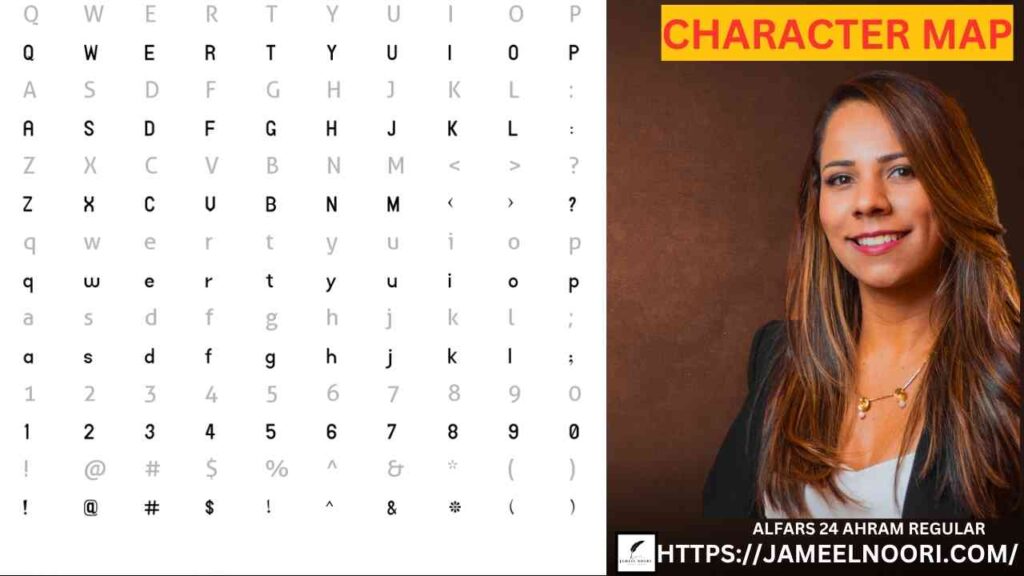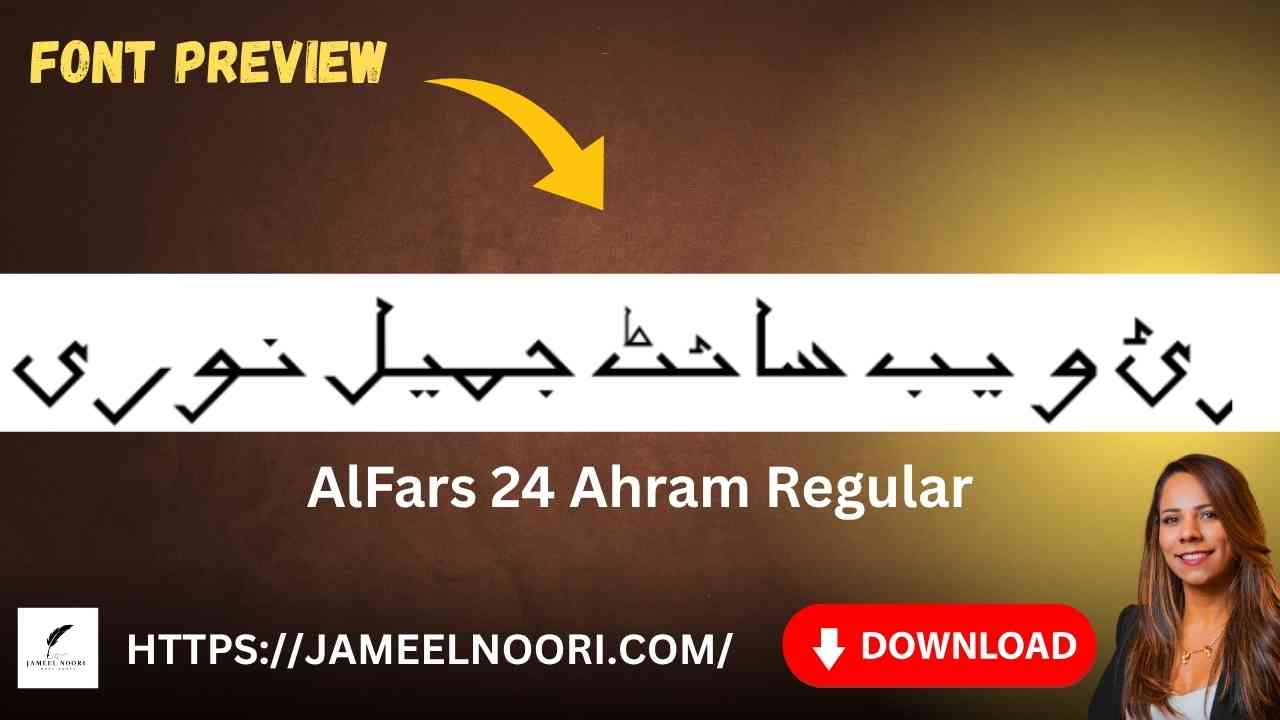
Introduction –Download Urdu Font AlFars Ahram Regular -Urdu Font Kya Hai?
Agar aap ek stylish aur graceful Urdu font ki talash mein hain jo digital aur print design dono ke liye perfect ho, to AlFars Ahram Regular aap ke liye ek behtareen choice hai.. Is Urdu TrueType Font ne designers aur Urdu lovers ke darmiyan apni khas jagah bana li hai, jise ab tak 12,782 baar download kiya ja chuka hai..
AlFars Ahram Font Ke Features
- ✅ Stylish aur readable Urdu script
- ✅ Ideal for digital graphics, posters, YouTube thumbnails
AlFars Ahram Urdu Font Use Cases
AlFars Ahram Regular font Urdu ke kai mukhtalif designs mein behtareen kaam karta hai:
- ✅ Urdu poetry aur quotes posters
- ✅ Social media Urdu posts
- ✅ Calligraphy & banners
- ✅ Book titles and print layouts
- ✅ YouTube thumbnails with Nasta’liq styling
Conclusion – Urdu Design Mein Naya Andaz
Agar aap Urdu typography mein modern look aur smooth readability chahte hain, to AlFars Ahram Regular Urdu Font ka istemal zaroor karein.. Yeh font aapke designs ko ek naya asar dega jo aapke viewers ko pasand aayega..